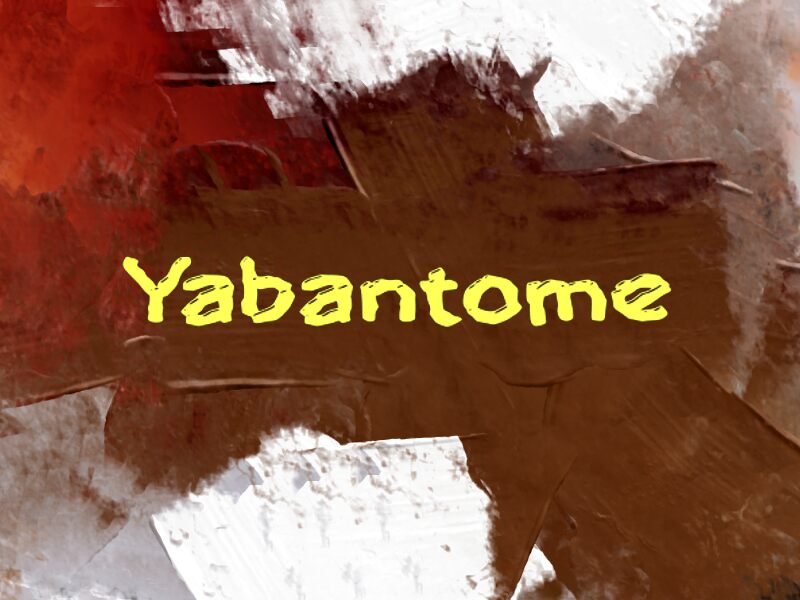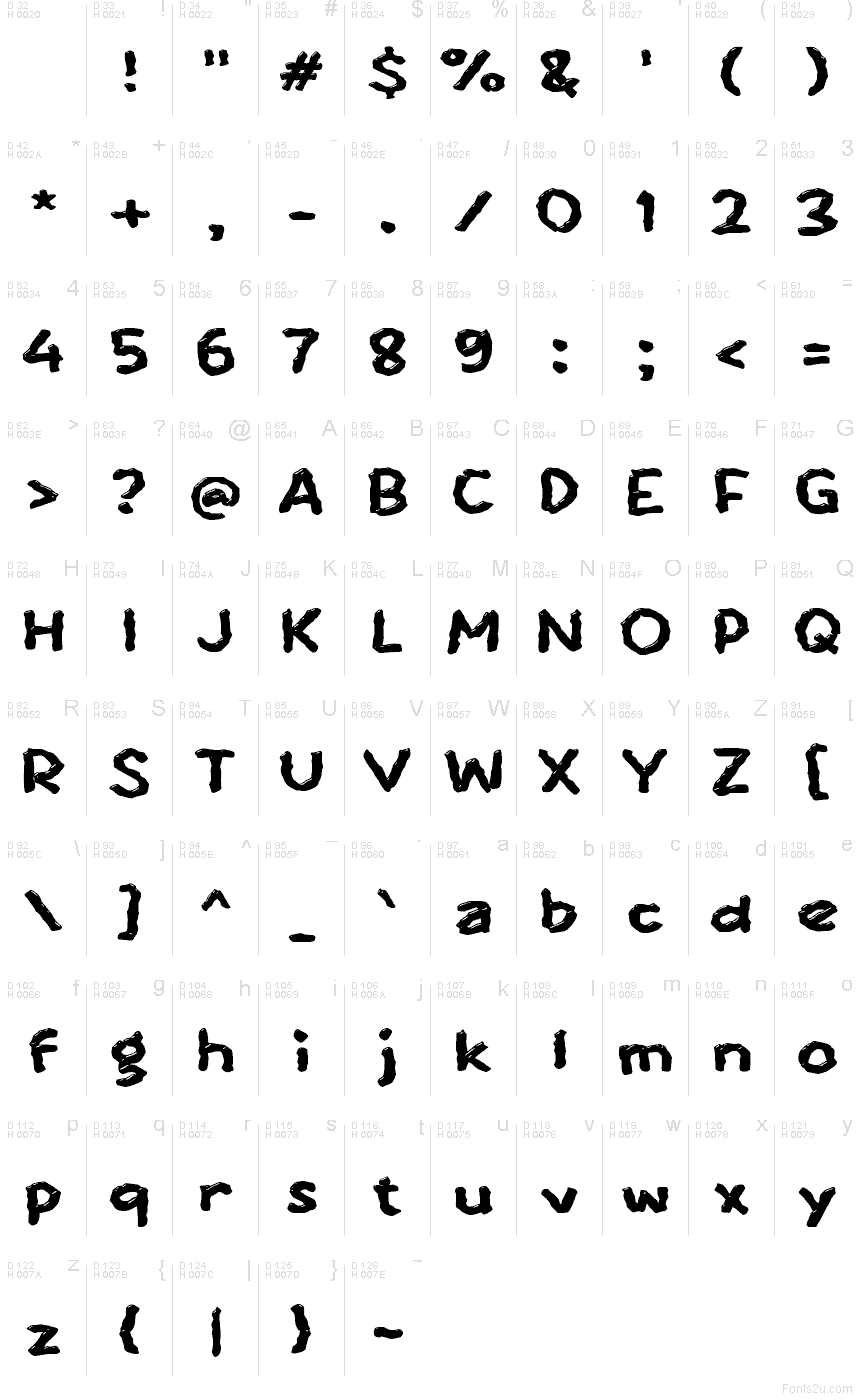
Yabantome od Wep to darmowy, wyrazisty krój pisma o surowym, ręcznie ciosanym charakterze. Litery wyglądają na spuchnięte i nierówne, z miękkimi narożnikami, masywnymi pociągnięciami i drobnymi wyszczerbieniami, dzięki czemu całość sprawia wrażenie wyrytej w korze, błocie lub namalowanej grubą warstwą farby, a nie zaprojektowanej na siatce.
To sprawia, że naturalnie pasuje do plakatów indie, logotypów gier, okładek zinów, klimatycznych opakowań oraz krótkich nagłówków, gdzie zbyt czyste wykończenie wydawałoby się zbyt grzeczne. Jako darmowy font świetnie sprawdzi się też na planszach tytułowych, w nazwach zespołów czy dużych cytatach, zwłaszcza gdy zależy Ci na pierwotnym, zabawnym i nieco nieokiełznanym efekcie.
Yabantome
Prezentacja i próbka wizualna czcionki Yabantome
Mapa znaków czcionki Yabantome
Mapa znaków czcionki Yabantome: Podstawowy łaciński, strona 1
Glify czcionki Yabantome — Podstawowy łaciński, strona 1